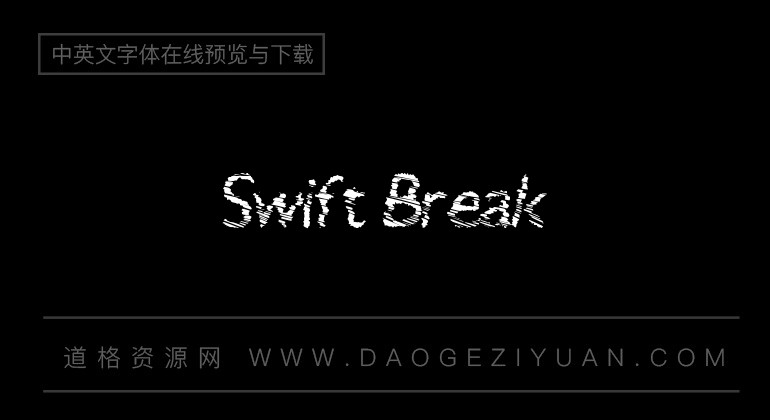
Swift Break 字体是一款拥有独特设计风格的字体,它使用非常简洁的线条来表达文字,具有现代感和精致的外观。Swift Break字体的设计灵感来自现代抽象艺术,它的线条精细,给人一种抽象的感觉,可以带来更多的创意想法。它可以用于文字、标题、标签等,可以为你的设计带来更多的创意。内容介绍
Swift Break是一款非常不错的手写艺术字体,具有很好的视觉感,适合于文化类的宣传设计、商业类品牌的广告和产品包装设计以及个性化文字排版等较多场景。